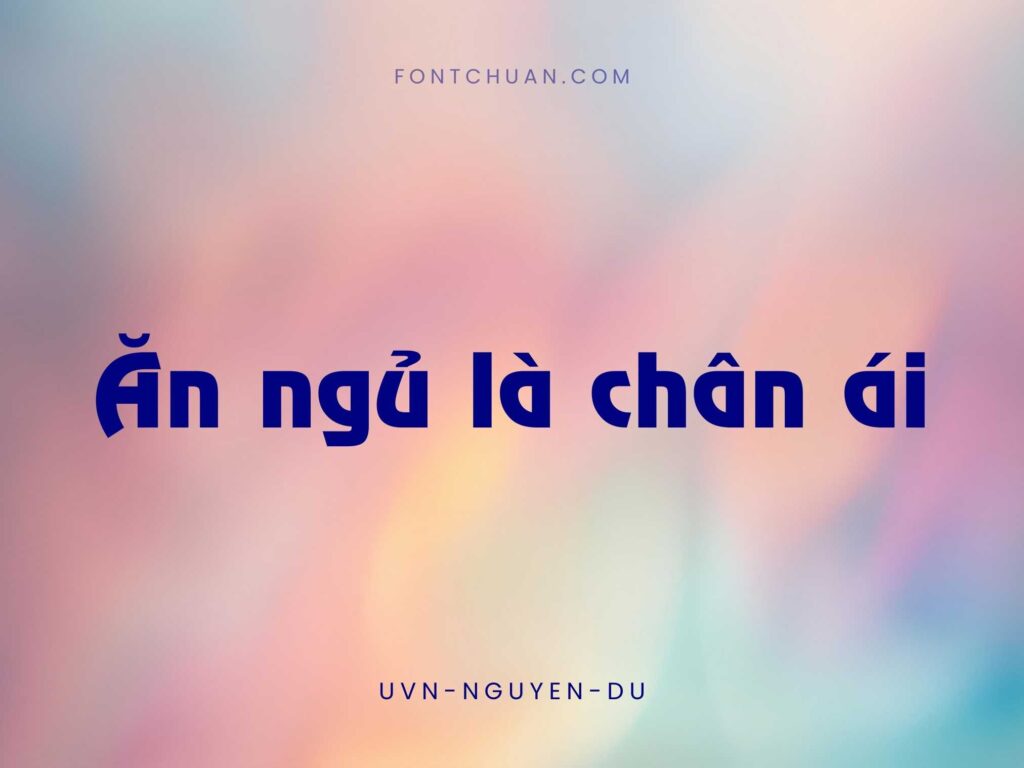
Font UVN Nguyen Du Việt Hóa
UVN Nguyễn Du là một phông chữ sans-serif mang phong cách hiện đại, được thiết kế bởi Tom Trương vào năm 2001. Phông chữ này có các đường nét đơn giản, rõ ràng và tinh tế, tạo nên sự thanh lịch và dễ đọc. UVN Nguyễn Du hỗ trợ đầy đủ các ký tự tiếng Việt, giúp người dùng dễ dàng sử dụng trong các dự án sáng tạo liên quan đến văn hóa Việt Nam.
Với thiết kế hiện đại và rõ ràng, UVN Nguyễn Du phù hợp cho các ứng dụng như tiêu đề, văn bản, thiết kế logo và các ấn phẩm truyền thông. Trong lĩnh vực sự kiện, phông chữ này có thể được sử dụng trong các dịp như hội thảo, triển lãm và các sự kiện doanh nghiệp. Ngoài ra, UVN Nguyễn Du cũng thích hợp cho các ngành nghề như thiết kế đồ họa, truyền thông và giáo dục.